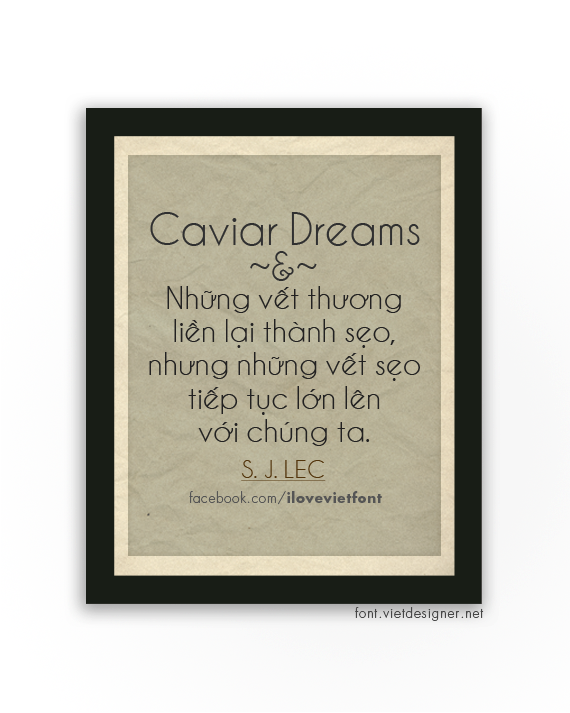
Việt hoá font dream scrip pro nghe cái tên là nhận thấy font rất đẹp rồi. Vnf caviar dreams tiếng việt phiên bản :
[sans serif] caviar dreams tiếng việt tháng một 29, 2013 trong font tiếng việt trả lời hủy trả lời điền thông tin vào ô dưới đây hoặc nhấn vào một biểu tượng để đăng nhập: Font chữ có tới 1000glyphs ở bản gốc, và gần 1500 glyphs với bản việt hóa. Trong quá trình việt hóa, khó tránh khỏi sai sót.
Caviar dreams mới cập nhật download Link tải 2000 font việt hóa mới nhất 2021 pass giải nén: Đi kèm với sự phá cách hiện đại và đẹp mắt, dễ đọc.
Caviar dreams font việt hoá i love viet font cao đẳng fpt polytechnic chính thức bắt đầu học kỳ summer 2020 vào ngày 18/5. Caviar dreams font việt hoá i love viet font Caviar dreams là một font chữ đẹp mắt với cấu trúc chữ đơn giản và tinh tế.
Font này được yêu thích trong một thời gian dài dùng cho nhiều loại thiết kế khác nhau. Utm caviar bộ font chữ việt sử dụng bảng mã unicode font (font family name: Nhận đăng kí việt hoá font cho các bạn yêu thích các bộ font nước ngoài nhưng chưa viết đk tiếng việt.